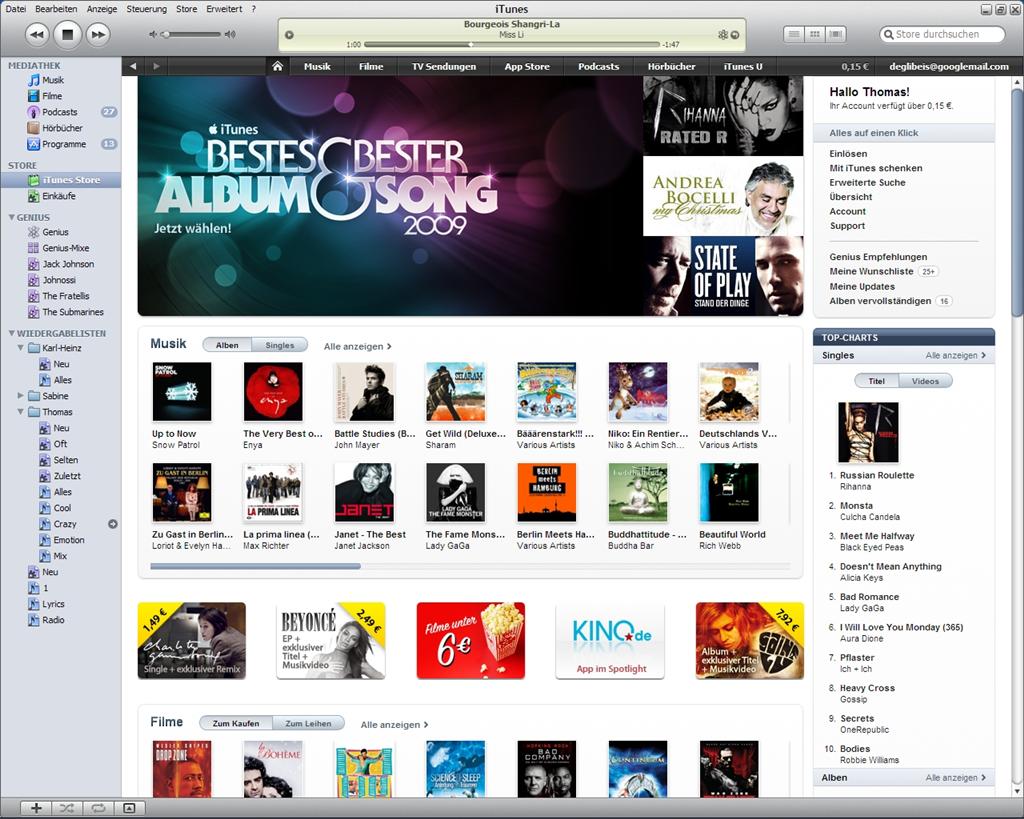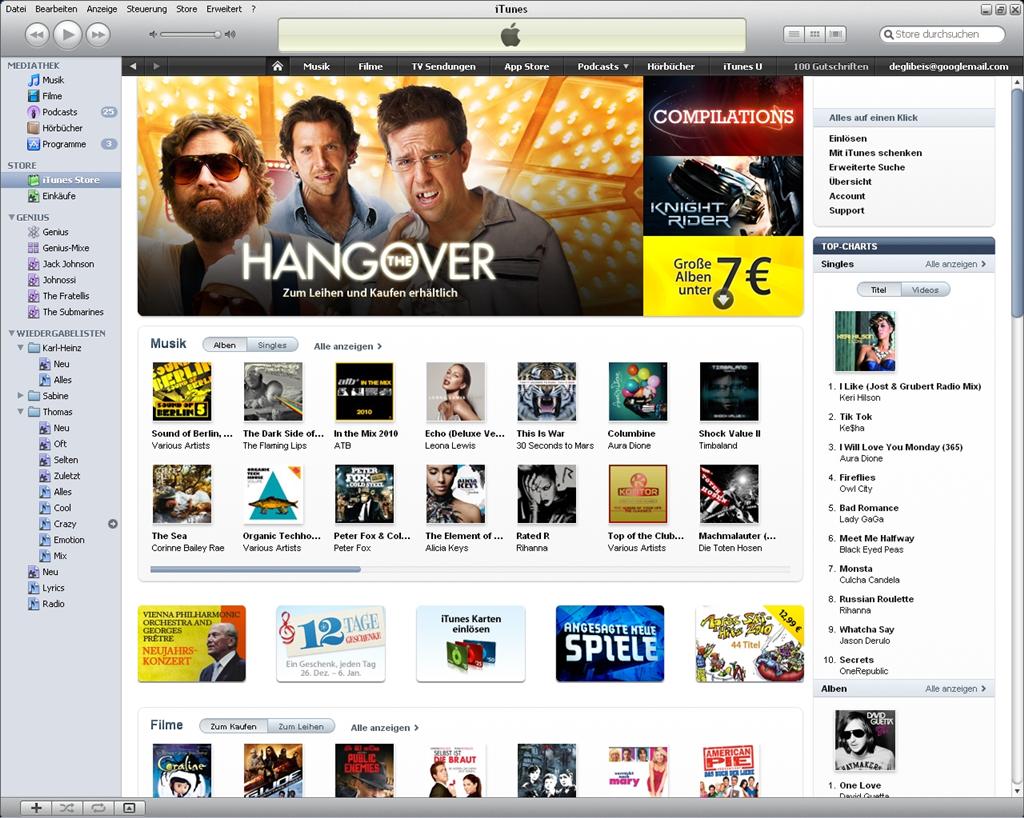
Andere Systemweite Schriftart?
Nachdem ich Windows XP neu installieren musste, wird überall eine andere/blöde/hässliche Schriftart verwendet. Z.B. der Text auf Websiten und die verschiedenen Dinge in der Seitenleiste bei iTunes. Die Schriftart die vorher verwendet wurde war weniger abgehackt und etwas fetter.
Ich hab zum Glück noch n' Screenshot von vorher. Aber man kanns darauf nicht ganz so gut erkennen.
Wie kann es sein das z.B. im Browser und in iTunes eine andere Schriftart verwendet wird?